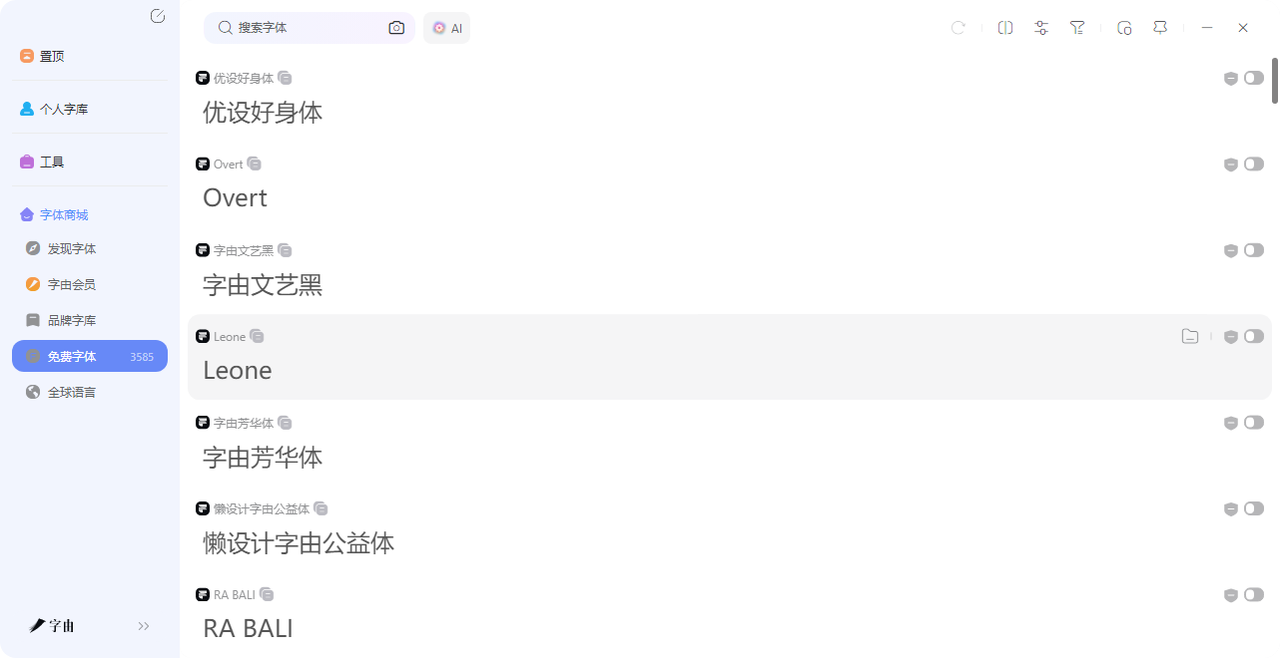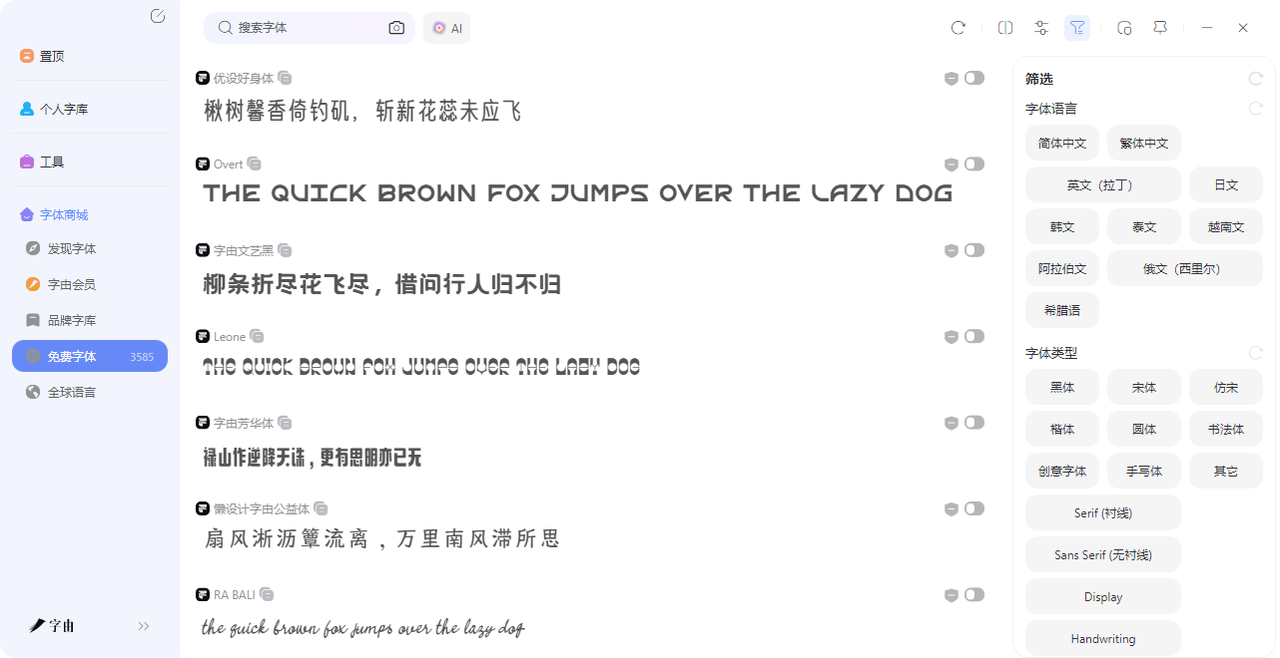
找字体不用愁,这几个网站一键搞定
做设计的人都知道,找字体这件事,有时候比做设计本身还费劲。明明脑海里已经有画面了,可就是找不到一款合适的字体来匹配。翻遍收藏夹,点开一个网站,分类太乱;换一个,下载还要注册;再换一个,全是英文,不知道怎么筛。折腾半天,灵感早跑没了。其实,找字体真的不用这么复杂,用对网站,分分钟就能定位到想要的那款。今天我就把私藏的4 个找字体网站一次性分享出来,每个都能让你快速地找到想要的字体。需要的直接收藏,以后找字体不用再发愁。
很多人用字由,只看到它字体多,却没发现它最好用的是找字体的筛选功能。字由收录了超过10500 款字体,其中3585 款是免费可商用的。但如果你不会筛,就会觉得“怎么这么多”。其实掌握下面3步,你就能在字由里精准定位到想要的那一款。
- 第一步:如果你想要免费的字体,可以打开字由客户端或网页版,点进“全部字体”,左侧(客户端是左侧栏,网页版在上端筛选)第一个要看的就是“授权范围”。如果你要商用,直接点“免费商用”,系统立刻从一万多款字体里筛出3585款。这个操作帮你排除了所有需要付费或授权不明的字体,剩下的随便用,不用担心侵权。如果你只是个人练习,也可以选“个人免费授权”。这一步是找字体最关键的一步,直接锁定可用范围。
- 第二步:在“字体类型”里,根据你的设计需求选择。做海报标题?点“黑体”或“书法体”。做文艺风?点“手写体”。做UI界面?点“Sans Serif”。做中国风?点“书法体”或“创意字体”。这一步帮你把范围从几千款缩小到几百款,更精准。
- 第三步:最后一步,你可以按“字体风格”筛选——想要国潮风点“中国风”,想要可爱点“卡通”,想要高级感点“简约”。或者直接按“热度”排序,优先选使用次数高的,比如“优设标题黑”超1000 万次使用,说明经过了大量设计师的检验。如果你还想更细,还可以按“字体品牌”(汉仪、蒙纳、Aa字库)、“字符集”(简体、繁体)、“字重”(纤细、正常、粗)、“字体语言”(中文、日文、韩文)来筛。
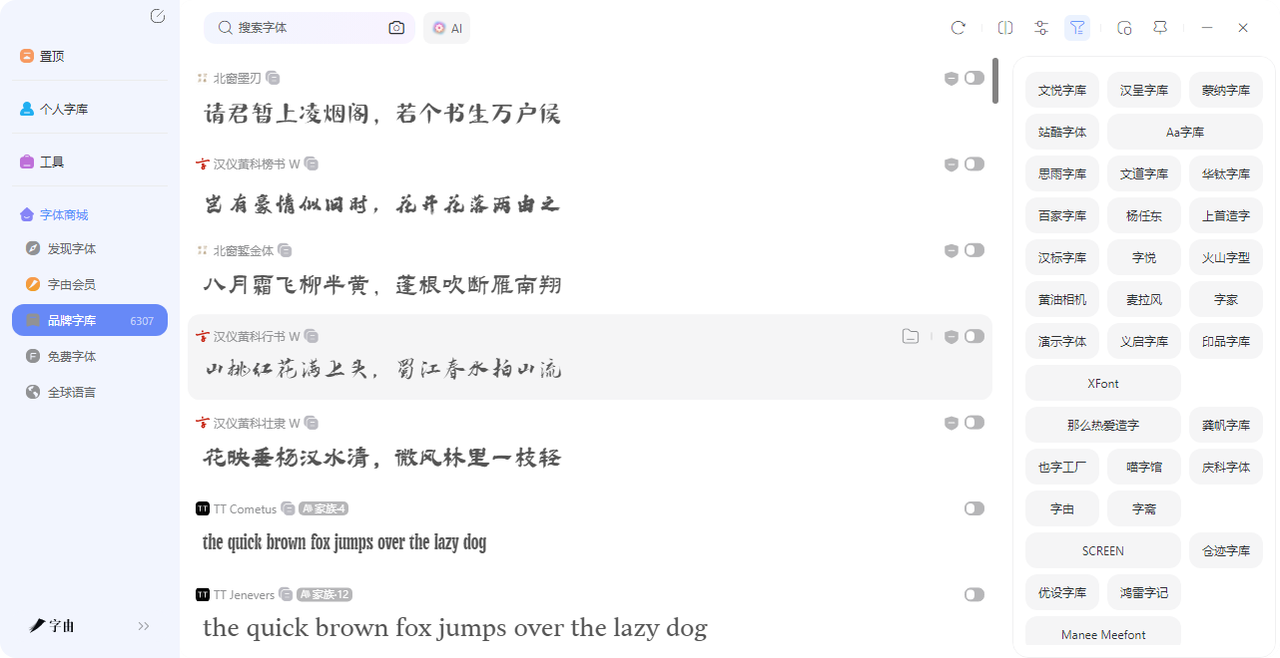
这三步走下来,你从一万多款字体里,精准锁定到几十款既符合授权又符合风格的设计,然后慢慢挑就行。
2、FontGet
这个网站也有着强大的分类筛选功能,是一个找字体体验极佳的网站,它的分类方式不是简单的风格,而是按使用场景划分。左侧导航栏分成了几大类,每个大类下又有细分,让你能根据项目需求快速定位:
- basic:sans serif、serif、italic等基础字体
- party:wedding、tattoo、birthday、baby shower、halloween、christmas
- old school:retro、vintage、typewriter、antique、medieval、old english
- style:3d、chunky、comic、calligraphy、cute、pixel
- fancy:cartoon、outlined、eroded、curly、horror、grid
- modern:techno、futuristic、science fiction、digital、blocky
这种分类可以大大地去节省我们找字体的时间,不用在一堆字体里漫无目地寻找,每个字体都有预览图,输入文字就能看到效果。下载前会标注授权类型,方便判断。
3、W3Schools
W3Schools 是一个知名的技术教程网站,它有一个“CSS Web Safe Fonts”页面,专门介绍网页安全字体。虽然它不是传统意义上的字体下载站,但对于网页设计师来说,这里找字体非常方便——它告诉你哪些字体是所有系统都有的,直接写在CSS里就能用,不需要下载。我比较推荐的几款字体有:
- Arial (sans-serif):最广泛使用的字体,也是Google Docs的默认字体,在所有主流系统上都可用。
- Verdana (sans-serif):非常流行的字体,即使在小字号下也清晰易读。
- Times New Roman (serif)、Courier New (monospace) 等。
每个字体都有示例和说明,还可以直接“Try it Yourself”在线测试。如果你做网页设计,需要快速确定正文或标题字体,这里是最快的参考站。
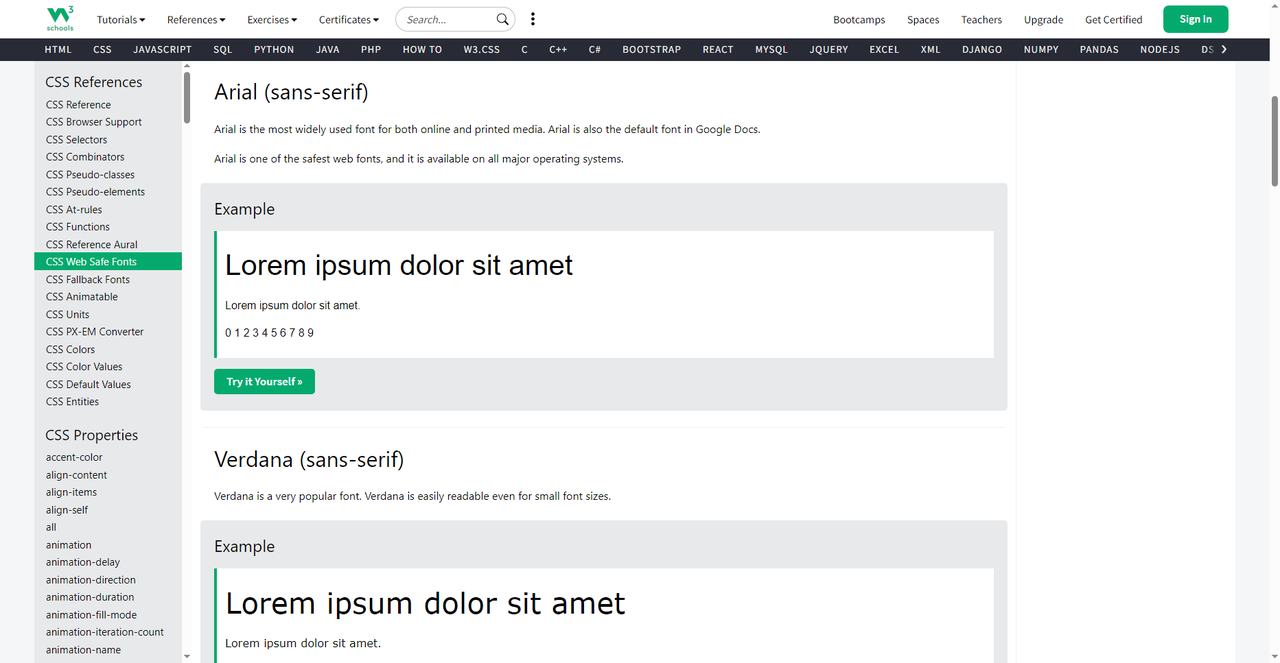
4、Awwwards
Awwwards 是全球知名的网页设计奖项平台,它专门整理了一个“Free Fonts”合集,收录了289款适合网页项目的免费字体。这里找字体的体验像逛设计展——每一款都是精心挑选,风格偏向现代、简约、有设计感。
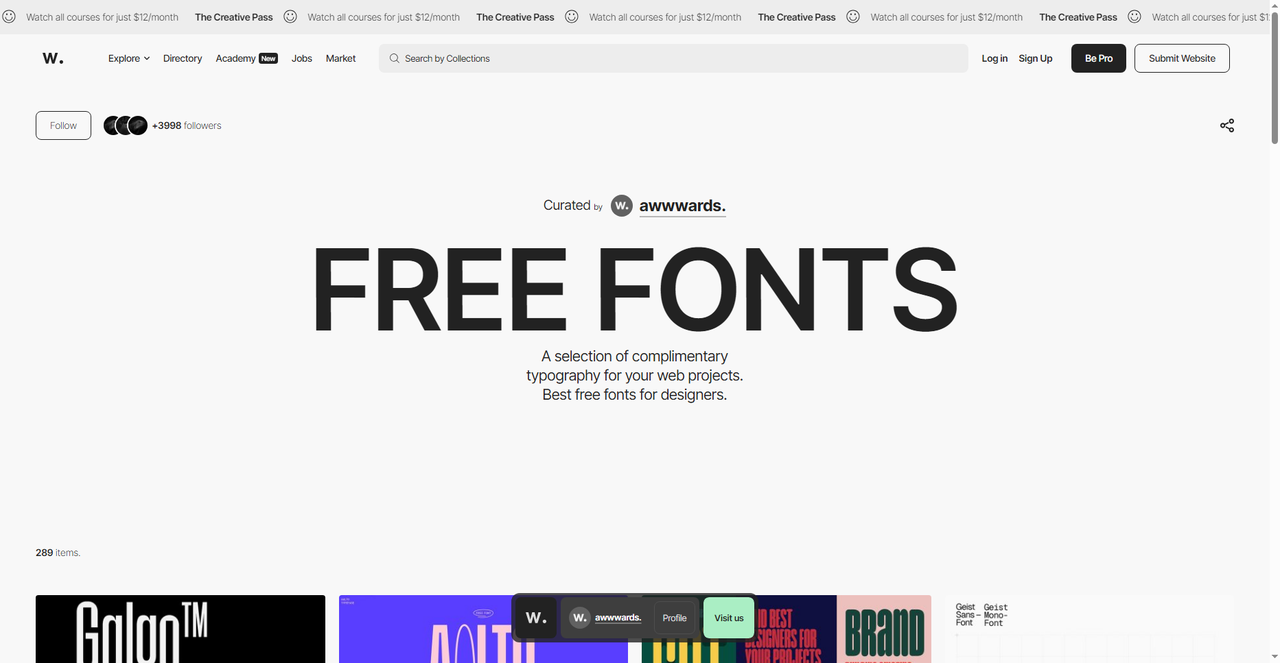
以上就是今天要介绍的一些重点使用的找字体网站了,简单的是,只要用对网站,就能把时间花在筛选而不是搜索上。这4 个找字体网站各有优点,但是我偏偏最喜欢字由,理由其实也很简单,因为字体不仅仅是一个字体网站,更是综合了众多实用功能于一体的万能网站,别的网站没有的字由就有,最主要的是学会用它的筛选功能,你就能在一万多款字体里精准定位到想要的那款,省下大量翻找时间。推荐你们都去试试字由!